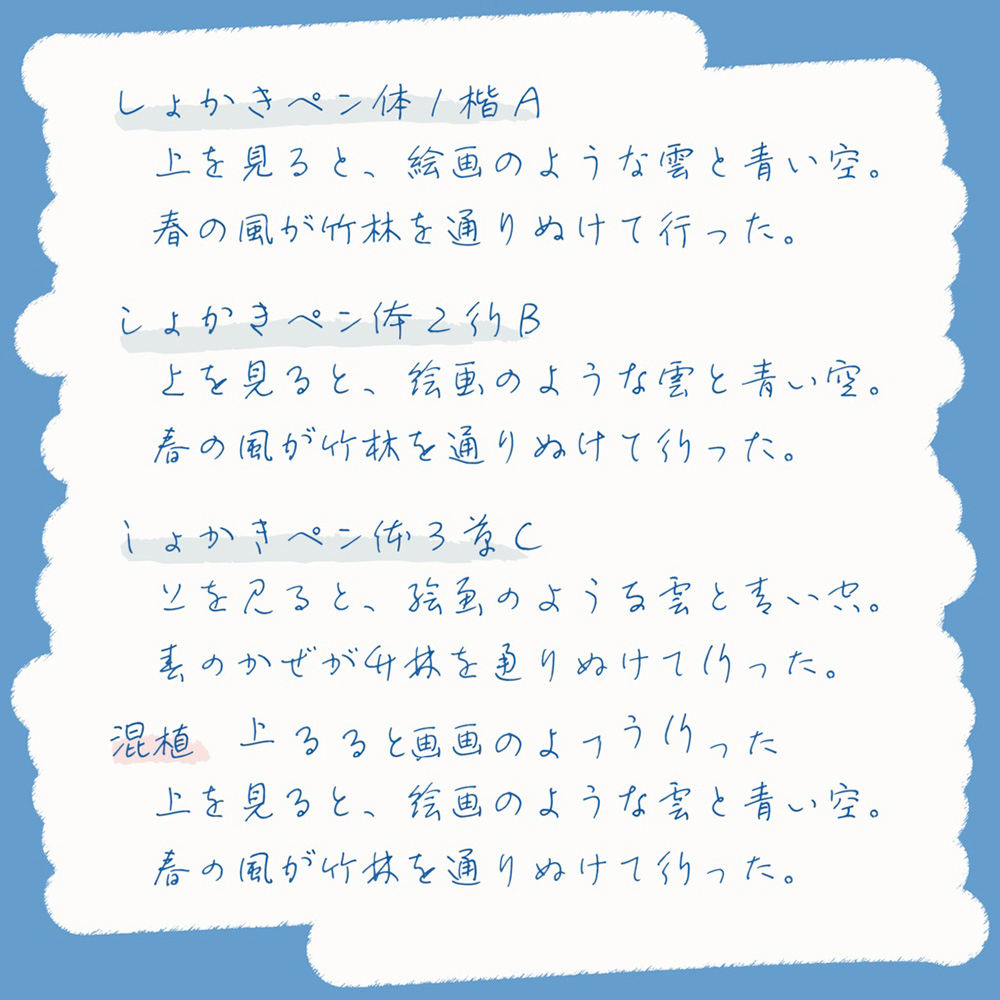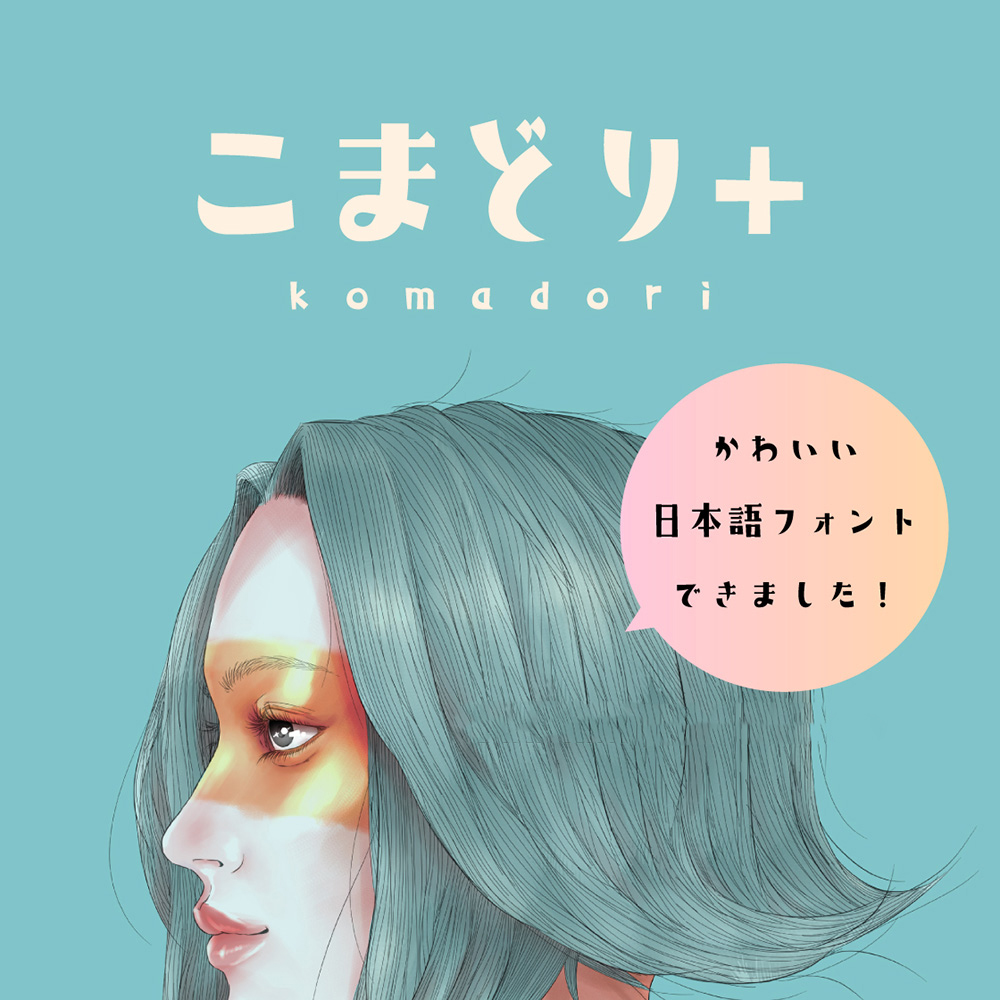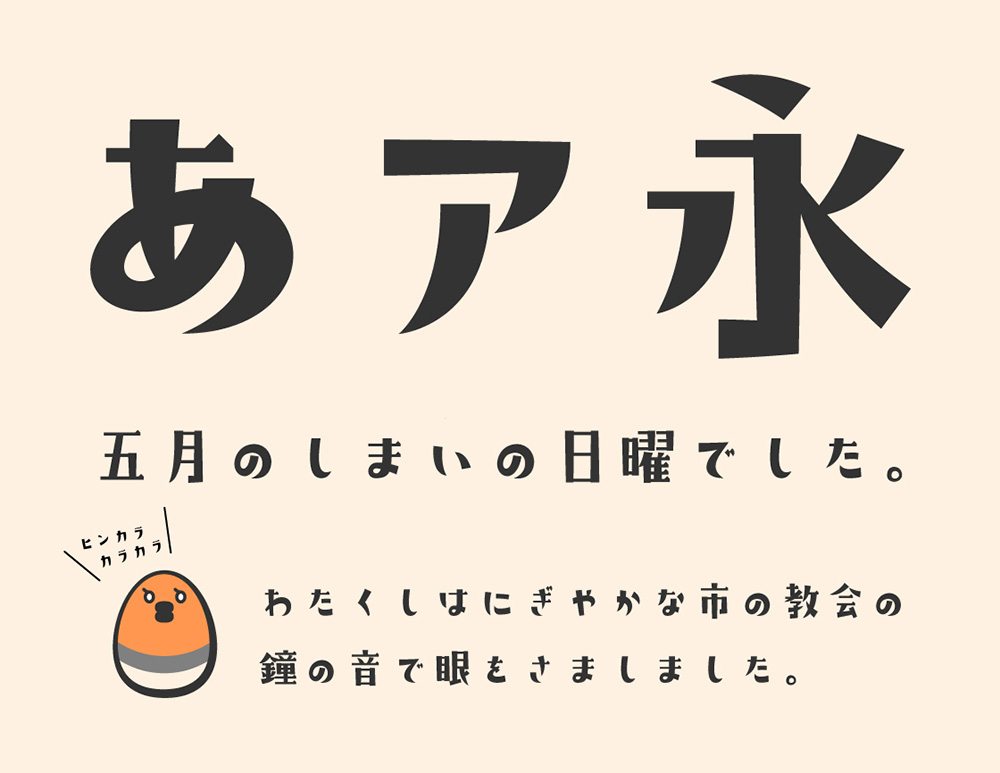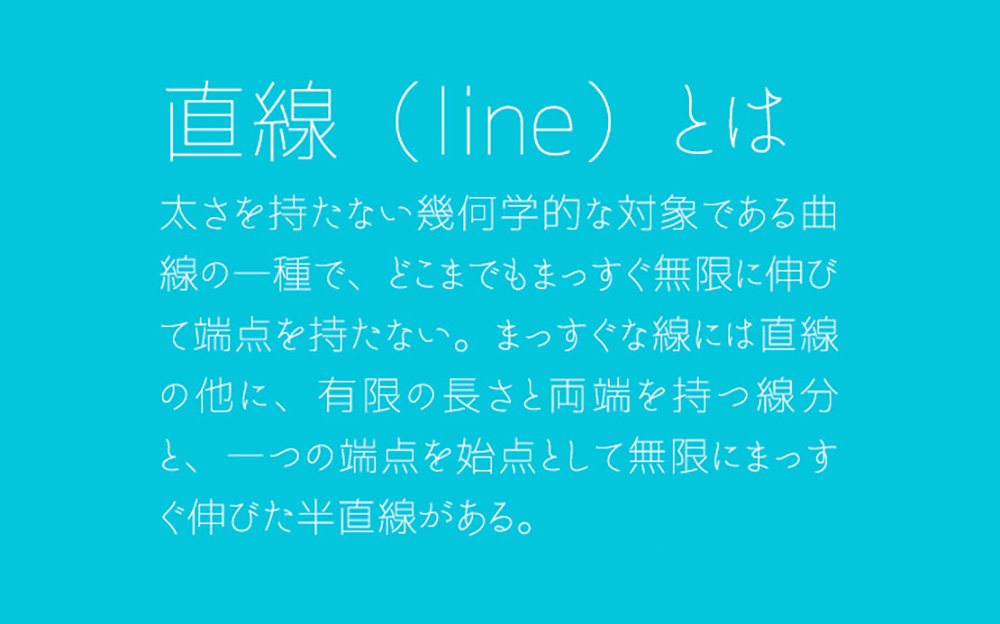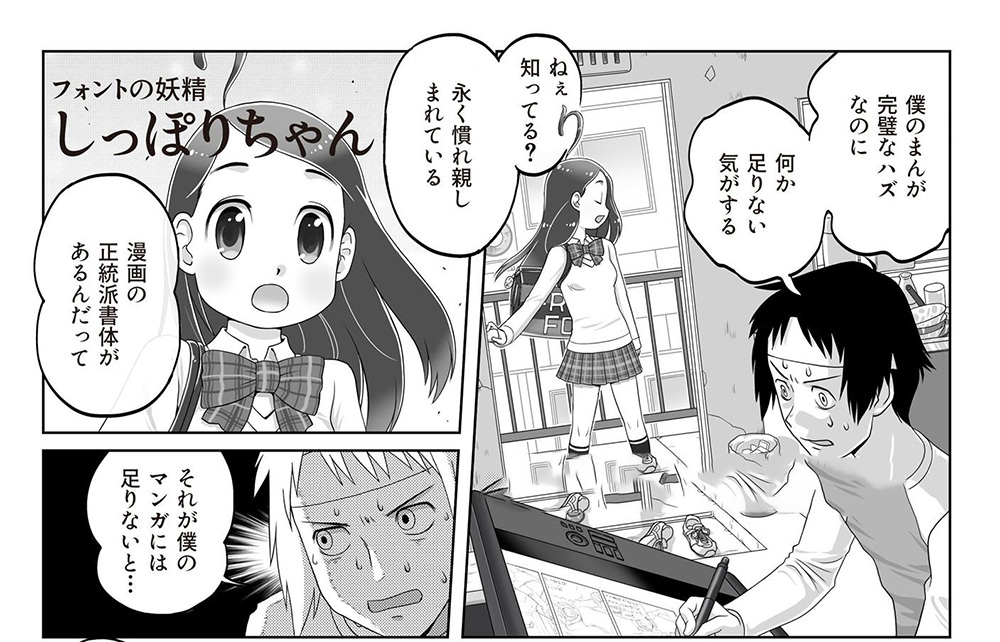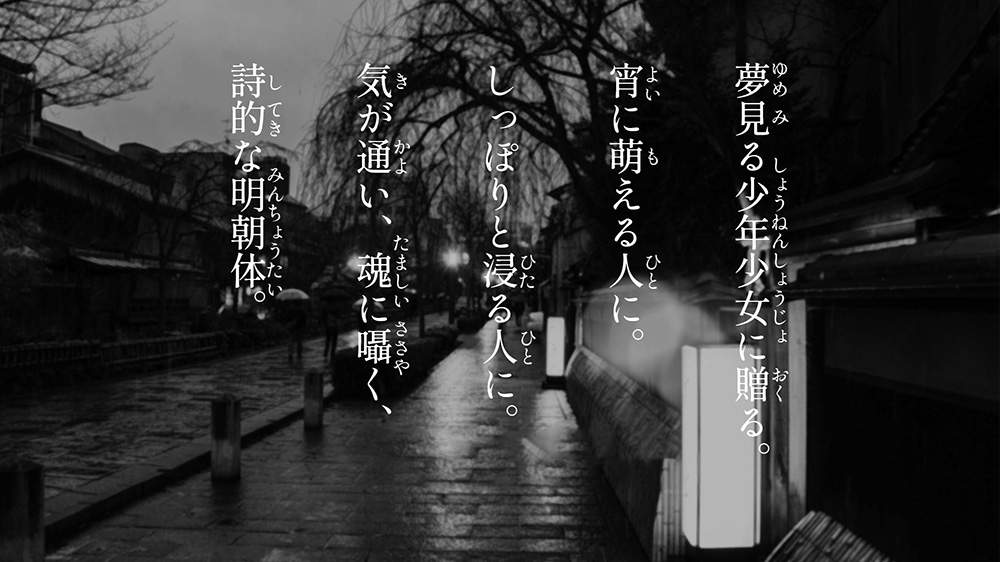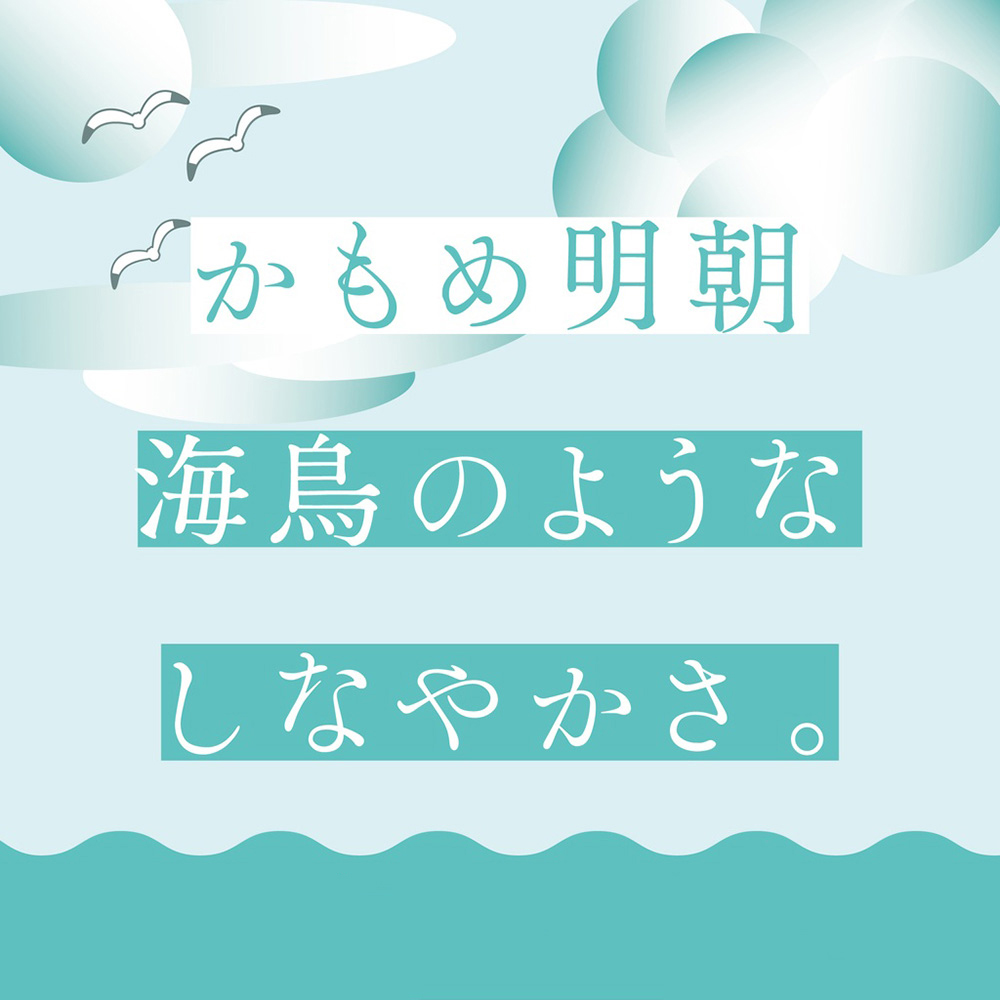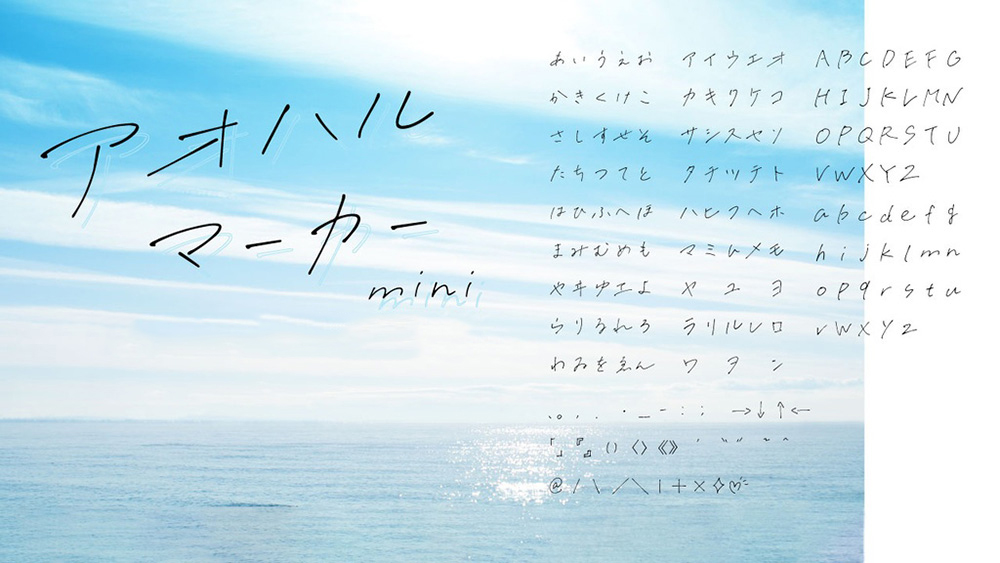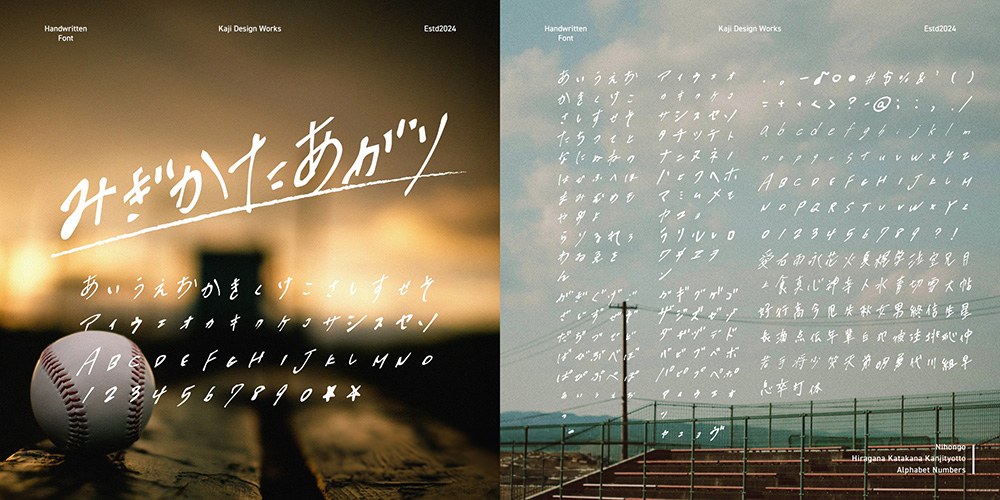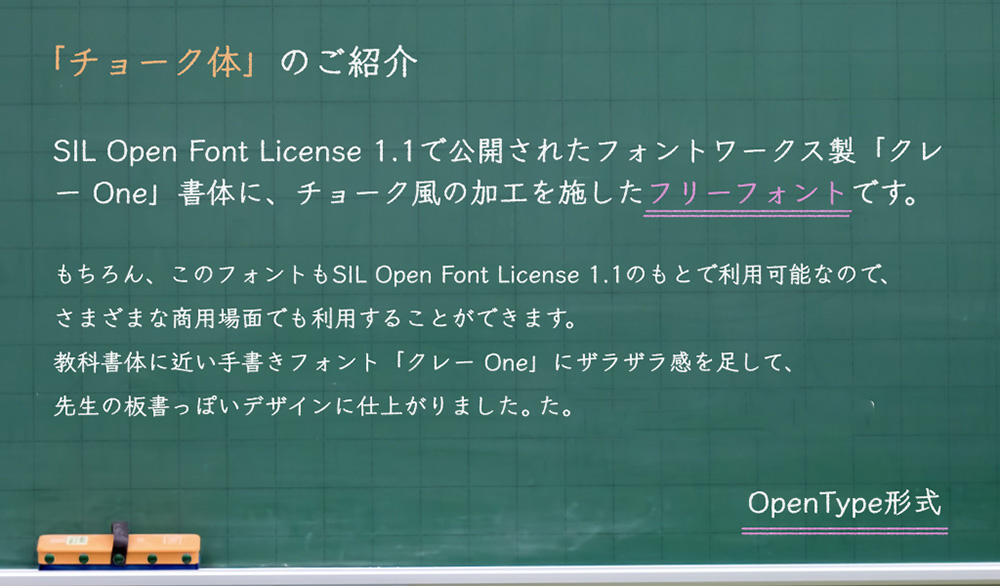
Download Free 10+ Font Chữ Nhật Thông Dụng
Sadesign.vn đã tổng hợp và cung cấp hơn 10 font chữ Nhật thông dụng hoàn toàn miễn phí. Đây là bộ sưu tập lý tưởng dành cho các nhà thiết kế, biên tập viên hay bất kỳ ai đang tìm kiếm các font chữ mang phong cách Nhật Bản để sử dụng trong dự án của mình.
Font chữ luôn đóng vai trò quan trọng trong việc thiết kế đồ họa, đặc biệt là khi bạn muốn thể hiện phong cách hoặc văn hóa của một quốc gia cụ thể. Trong số đó, các font chữ Nhật Bản ngày càng được yêu thích bởi tính thẩm mỹ độc đáo và khả năng truyền tải tinh thần văn hóa Nhật Bản một cách chân thực. Tổng hợp 4 lý do bạn nên tải font chữ Nhật tại web sadesign.vn như sau:
1. Đa dạng và thích ứng nhiều nhu cầu thiết kế
Bộ sưu tập bao gồm nhiều kiểu dáng khác nhau, phù hợp với nhiều nhu cầu thiết kế khác nhau. Bao gồm từ cổ điển đến hiện đại, giúp bạn dễ dàng lựa chọn font chữ phù hợp với mục đích sử dụng.
4. Ứng dụng linh hoạt
Các font chữ này có thể được sử dụng trong nhiều lĩnh vực như thiết kế logo, banner, poster, thiệp mời, hoặc thậm chí là các sản phẩm in ấn mang phong cách Nhật Bản.